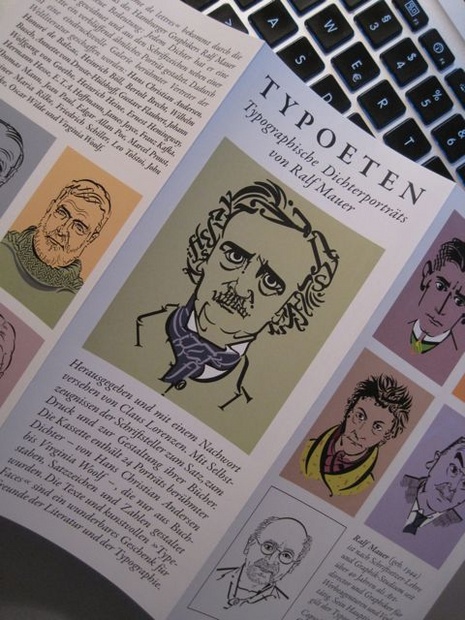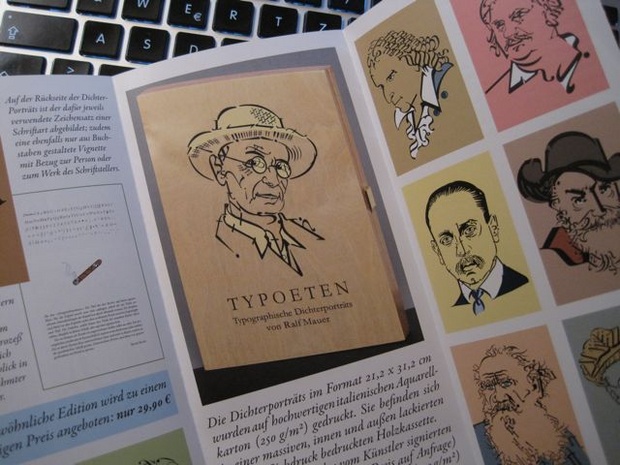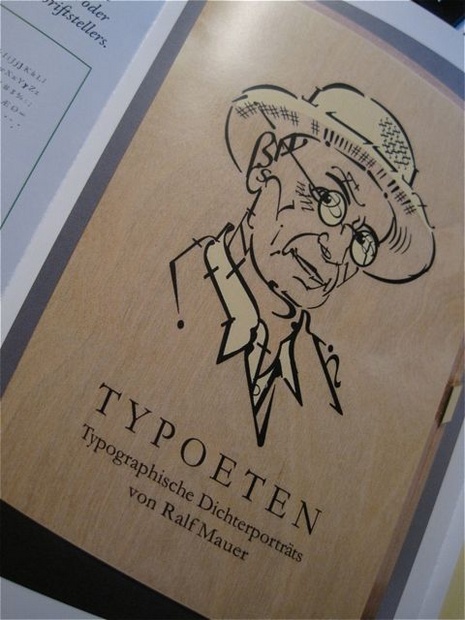
TYPOETEN Typographische Dichterportraits
ich war am Wochenende im Altonaer Museum in Hamburg und habe mir eine kleine feine Illustrationsausstellung angeschaut (bei der wunderbarerweise alle Illustratoren persönlich anwesend und in Plauderlaune waren).
Ich habe dort die Arbeiten von Ralf Mauer entdeckt und möchte Euch gerne teilhaben lassen an meiner Entdeckung. :-D Der sympathische Schriftsetzer und Grafiker hat mit ausschließlich typografischen Mitteln (Buchstaben, Satzzeichen und Zahlen) eine Reihe sehr schöner Dichterportraits geschaffen. Jedem Dichter hat Mauer eine Schriftart gewidmet und daraus dessen Portrait gestaltet. 24 Motive wurden auf feinsten Aquarellkarton gedruckt und befinden sich in einer schönen, siebbedruckten Holzkassette, die beim Künstler käuflich erworben werden kann. Ich bin von den Motiven und der liebevollen Ausgestaltung der Bögen wirklich entzückt und habe sie mir direkt zu Weihnachten gewünscht. Falls Ihr neugierig geworden seid: Weitere Informationen gibt es hier.
Ich kenne sonst nur Bildern aus ganzen Wörtern, sind echt schöne Werke entstanden
Ich mag ja eigentlich dieses Herumgebastel mit Buchstaben nicht so, aber die Portraits scheinen ganz gut zu funktionieren. Respekt.
Stimmt, ist ja auch ein tolles Thema. Ich finde, dass die Arbeiten von Ralf Mauer eine besondere gestalterische Qualität aufweisen und auch kompositorisch und farblich halte ich sie für ausgesprochen gelungen – sie sind (so weit ich das beurteilen kann) feiner und sensibler ausgearbeitet als die Beispiele auf »Words at Play«. Bei der Ausstellung habe ich die Drucke im Original gesehen und bin neben der künstlerischen auch von der handwerklichen Qualität sehr angetan. :-)
Keine Frage, da steckt viel mehr Arbeit und Können dahinter. »Words at Play« ist und bleibt eben eine Spielerei.Wobei ich ja gestehen muß daß ich gerade im Vergleich fasziniert davon bin mit wie wenig Zeichen man doch ein relativ treffendes Portrait erstellen kann.
geht mir auch so, größtenteils wirkt es immer sehr erzwungen.
aber hier stimmt das zusammenspiel weil die illustrationen nicht komplett aus
buchstaben zusammengesetzt sind.
Stimmt, Satzzeichen und Zahlen sind auch noch mit dabei. Aber sonst nichts.
Stimmt, Arno Schmidt hätte man gut in eine Reihenfolge mit Poe bringen können.